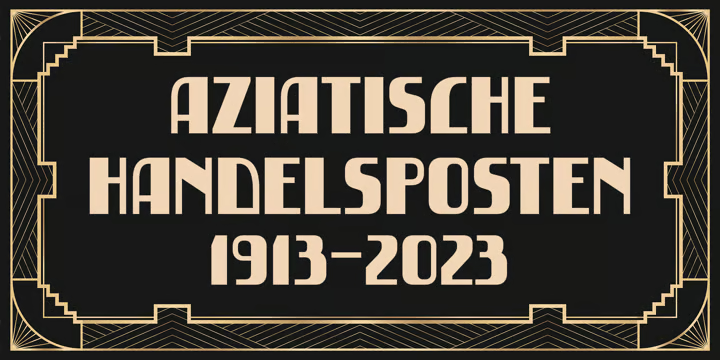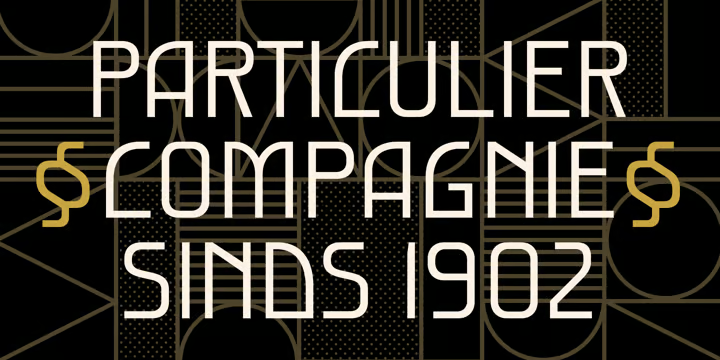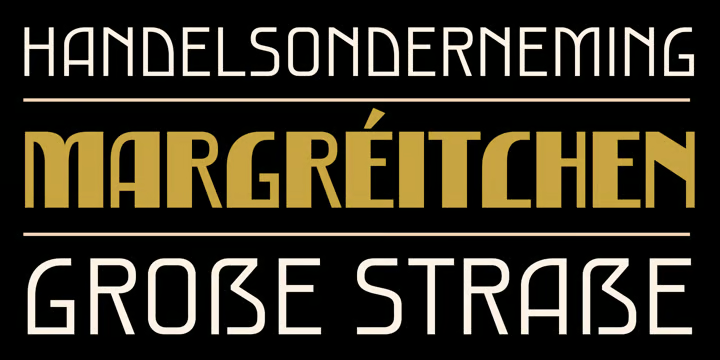
Potenciarte Font Family
Potenciarte est une police d’affichage en majuscules inspirée de la façade des vieux bâtiments de l’époque du Nederlandsch-Indie (années 1900) à Surabaya, où les styles typographiques Art déco et Art nouveau étaient largement utilisés.